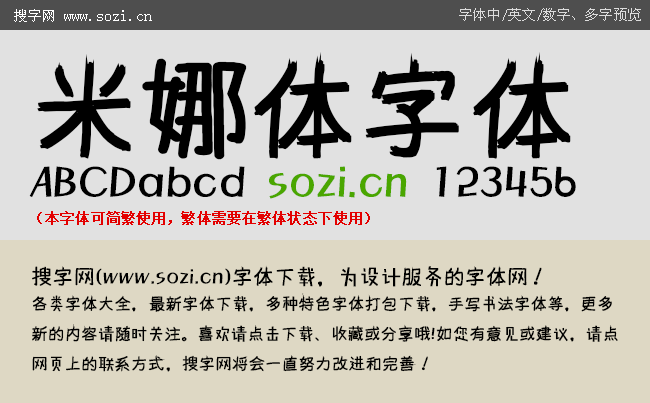
米娜體字體
搜字網(wǎng)給大家提供一款很帶有手寫風(fēng)格的手機(jī)中文字體下載。修改者將它命名為米娜體字體,這款手機(jī)字體是在帶有馬克筆效果的手寫風(fēng)格字體。極富趣味性,又有手寫字體的藝術(shù)性,特別適合喜歡手機(jī)字體個(gè)性一些的朋友在手機(jī)上安裝使用。